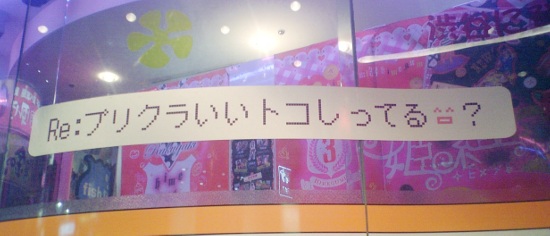
携帯(というか、ケータイというか)をイメージさせる書体といえば、やっぱりビットマップの書体。
こんな風に Re: や顔文字までついていれば、見ただけでピンとくる。
といっても、自分が初めて携帯を持ったのは5年ほど前だが、その頃には既にアンチエイリアスの掛かったフォントになっていた。そして今では、リュウミンやらヒラギノやら、さらにはAXISが入った携帯まで発売されている。
今の小中学生には、「携帯⇔ビットマップフォント」という連想は通じないかもしれない。